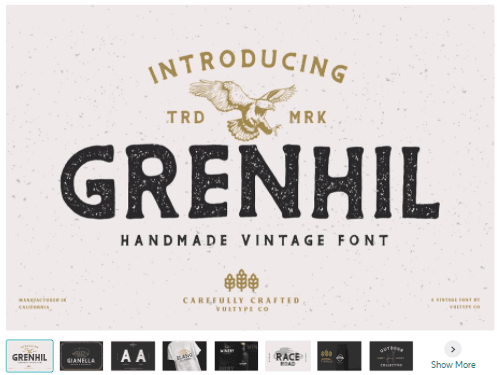
Grenhil - Handmade Vintage Font
Представляем Grenhil - старинный шрифт ручной работы
Grenhil - это винтажный ретро-шрифт без засечек с двумя стилями шрифта, включая обычный и грубый.
Тщательно изготовленные для создания идеальной текстуры и подходящие для каждого из ваших проектов, также отлично подходят для логотипов, дизайна брендов, дизайна логотипов, цифровых надписей, футболок / одежды, плакатов, журналов, вывесок, рекламного дизайна и любого винтажного дизайна.